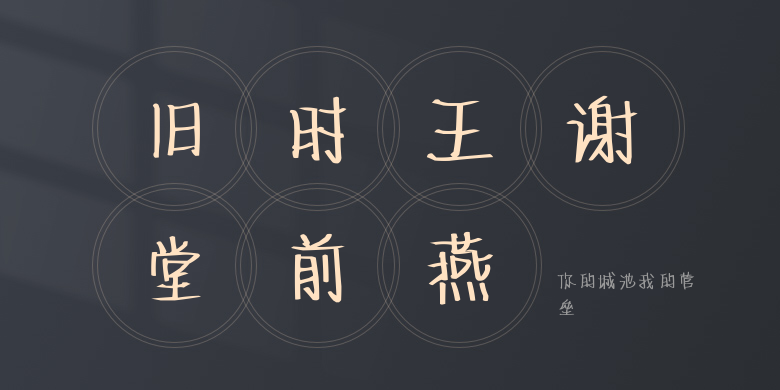
你的城池我的营垒
你的城池我的营垒,这款字体结构工整、笔画清晰,兼顾美观与易读性,适用于标题、正文、海报、包装、LOGO 等多种场景。字形优雅稳定,风格百搭耐看,适配日常排版与创意设计,让文字呈现更舒适、更具质感。你的城池我的营垒一笔一画,皆是细节,以均衡的比例、流畅的线条打造舒适视觉体验,字形端正大气,风格简约现代。无论是商业设计、品牌宣传还是日常排版,都能轻松驾驭,让文字更有格调与力量。你的城池我的营垒字体下载。